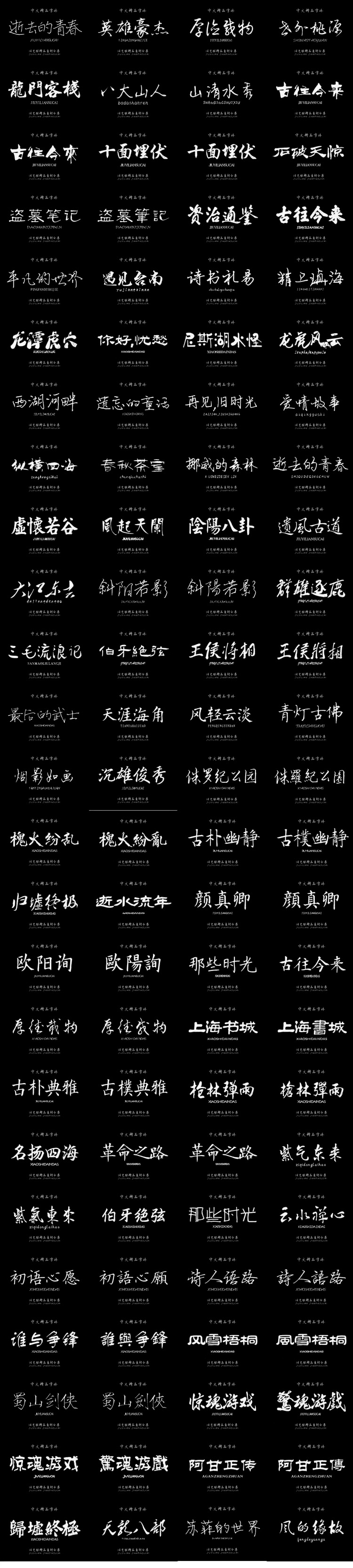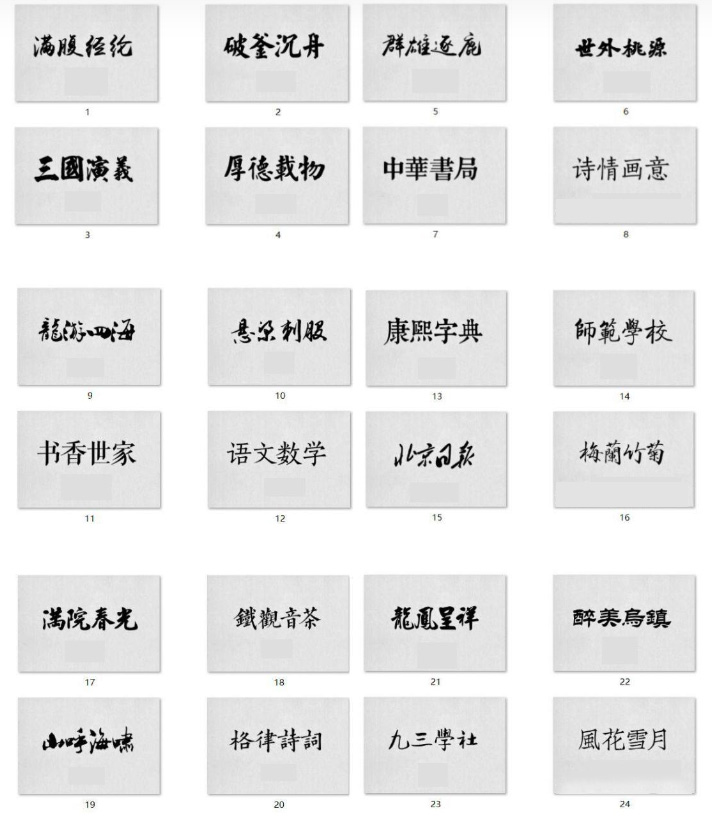
【分享】300多款古风毛笔书法字体,让你的设计作品更出彩!
在追求文字之美的旅途中,古风字体如同一股清泉,潺潺流淌于现代设计的心田。
本文分享精选的300款古风字体,这些字体,或遒劲有力,如碑刻般沉稳;或温婉细腻,似丝绸轻拂心间。它们不仅承载着千年的文化底蕴,更在现代设计的舞台上焕发出新的生命力。
300款书法字体
从宋体的典雅到楷书的端庄,从行书的流畅到草书的奔放,每一款字体都是对古代书法艺术的致敬与传承。
在这场视觉与文化的双重盛宴中,人们不仅能领略到古风字体的独特魅力,更能感受到中华文化的博大精深。
这300款古风字体,不仅是设计的灵感源泉,更是连接古今的文化桥梁。